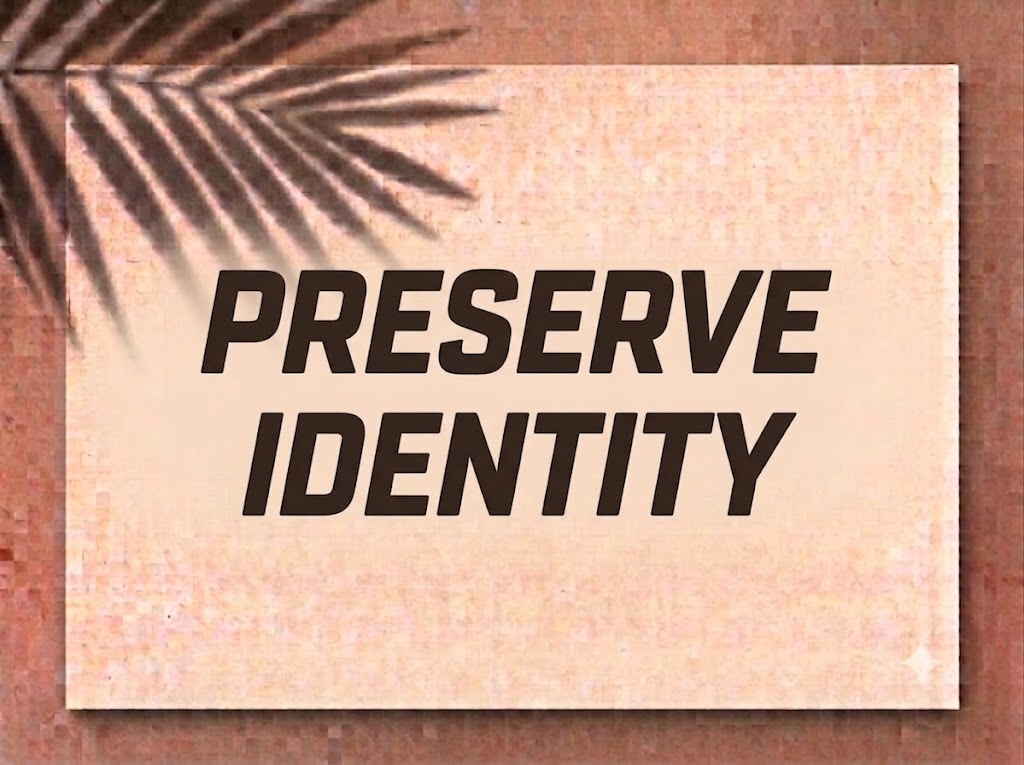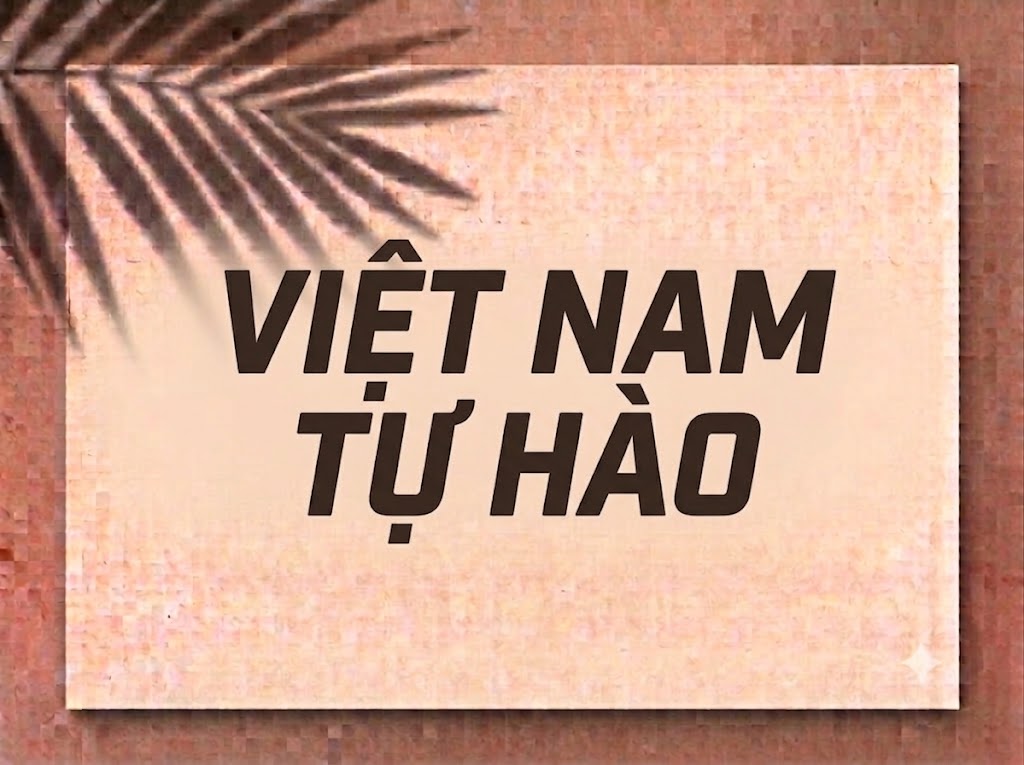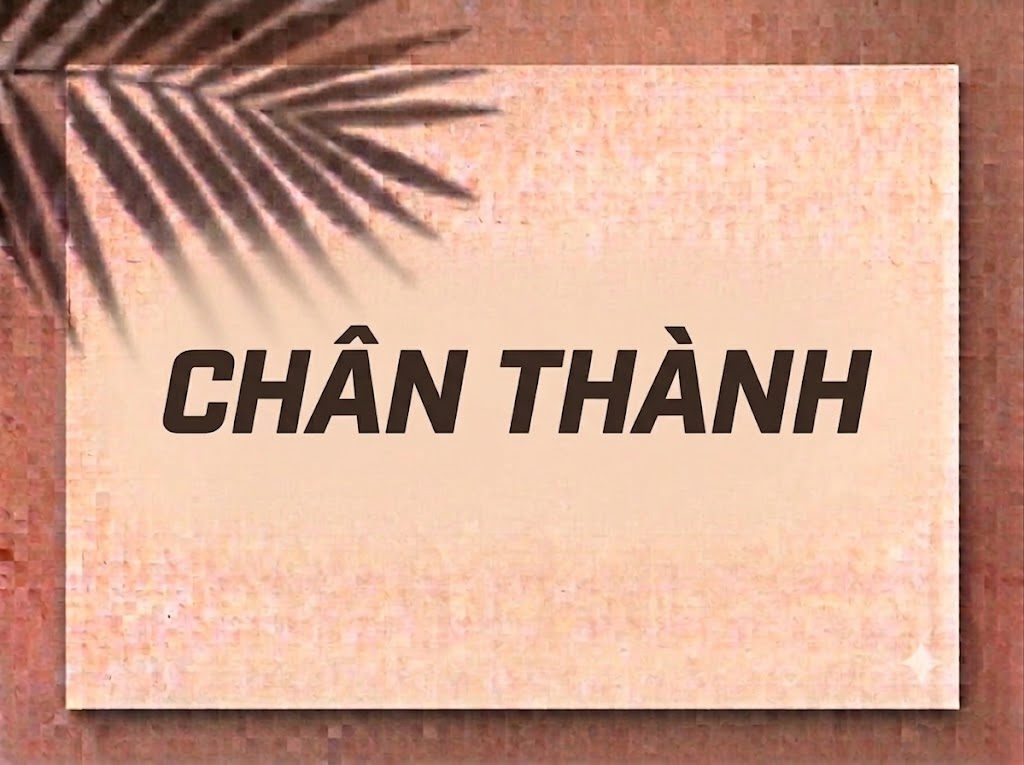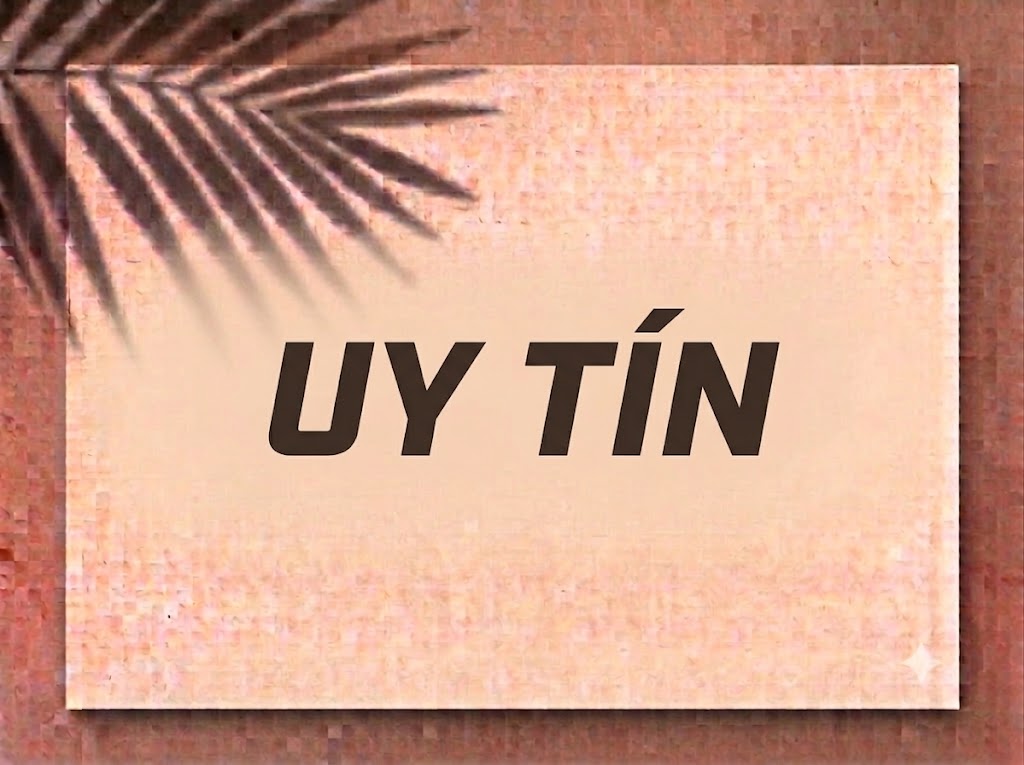
Trong thiết kế đồ họa thể thao, eSports, game và công nghệ tương lai, những phông chữ dáng nghiêng kết hợp với kết cấu khối dày dặn luôn tạo ra hiệu ứng thị giác mạnh mẽ. Chúng truyền tải được cảm giác tốc độ, sự chuyển động liên tục và tinh thần bứt phá cho các tiêu đề quảng cáo.
Nếu bạn đang tìm kiếm một phông chữ hiển thị nghiêng hầm hố, đậm chất kỹ thuật số để làm nổi bật thiết kế banner, thumbnail hay video ngắn, font 1FTV Designer chính là sự lựa chọn không thể bỏ qua.
Giới thiệu về font 1FTV Designer
Font 1FTV Designer là bộ chữ hiển thị không chân mang phong cách hình học nghiêng khối, kết hợp giữa sự vững chãi của nét chữ nét đậm và nhịp điệu tốc độ linh hoạt:
Tên phông chữ: 1FTV Designer
Được tối ưu hóa hoàn chỉnh về mặt kỹ thuật, phông chữ mang lại khả năng hiển thị vô cùng mượt mà. Bạn có thể phóng lớn tiêu đề trên các ứng dụng đồ họa chuyên nghiệp hay phần mềm dựng phim mà không lo gặp lỗi răng cưa hay vỡ nét.
Đặc điểm nổi bật của phong cách thiết kế Designer
Sức hút thị giác của font 1FTV Designer đến từ phom dáng nghiêng thể thao và nét khối dày dặn:
Phom dáng nghiêng tạo cảm giác tốc độ: Độ nghiêng vừa phải kết hợp với nét chữ khối tạo ra hiệu ứng chuyển động mạnh mẽ, rất phù hợp cho các tiêu đề thể thao hay gaming.
Định dạng All-Caps đồng bộ: Cả hai hàng ký tự trên phông chữ đều được xây dựng theo dáng chữ in hoa, giúp câu tiêu đề có chiều cao đồng đều, tạo thành một khối chữ kiên cố và dứt khoát.
Bo góc hình học tinh tế: Các góc ngoài ký tự được bo nhẹ giúp nét chữ giảm sự thô cứng, trong khi cấu trúc mảng khối bên trong vẫn giữ nguyên sự nam tính và góc cạnh.
Khoảng cách giữa các chữ (kerning) và độ giãn dòng nghiêng được tính toán chuẩn xác, giúp các mảng chữ nét đậm khi đứng sát nhau không bị dính nét.
Tích hợp trọn vẹn dãy chữ số 0-9 phom khối nghiêng đồng bộ cùng bộ ký tự đặc biệt, dấu câu thông dụng.
Bản Việt hóa chuẩn chỉnh giúp bạn hoàn toàn yên tâm thiết kế các câu tiêu đề tiếng Việt có dấu mà không gặp lỗi nhảy font hay mất ký tự.
Hình ảnh demo thực tế của font 1FTV Designer
Khả năng hiển thị của phông chữ này được tối ưu rất tốt trên nhiều tỷ lệ kích thước:
Kích thước nhỏ (12pt – 24pt): Cấu trúc chữ nghiêng ngay ngắn giúp câu chữ và dãy số vẫn hiển thị rõ ràng trên màn hình di động.
Kích thước lớn (36pt – 72pt): Đây là đất diễn lý tưởng nhất để 1FTV Designer phô diễn toàn bộ sự hầm hố, tốc độ và độ dày nét, tạo tác động thị giác mạnh cho các dòng tiêu đề.
Ứng dụng trong thiết kế đồ họa và làm video
Sở hữu nét cá tính bứt phá và giàu năng lượng, font 1FTV Designer mở ra không gian ứng dụng phong phú:
Video ngắn (TikTok, Reels, Shorts): Phông chữ nghiêng khối này hiển thị rất bắt mắt trên khung hình đứng tỷ lệ 9:16, giúp câu giật tít thu hút người xem dừng lướt feed ngay lập tức.
Ảnh thu nhỏ YouTube (Thumbnail): Lựa chọn hàng đầu cho các kênh thể thao, đua xe, eSports, review công nghệ hay trailer phim hành động nhờ độ nhận diện cao từ xa.
Banner quảng cáo và Poster sự kiện: Hoàn hảo cho các poster giải đấu game, chương trình khuyến mãi sự kiện, banner gym fitness hay các ấn phẩm truyền thông sôi động.
Nhận diện thương hiệu Streetwear & Tech: Thích hợp làm logo dạng chữ khối, nhãn mác bao bì sản phẩm hoặc in ấn artwork trên áo thun cho các thương hiệu cá tính.